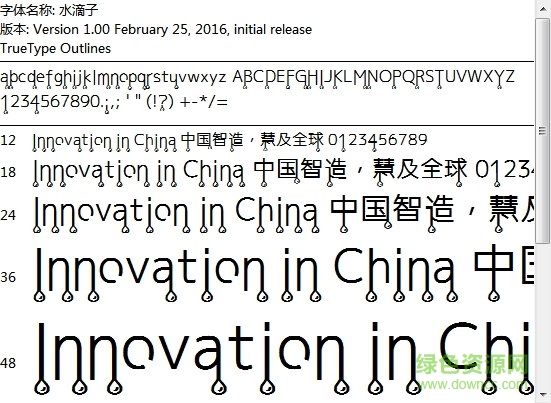
水滴子字體
水滴子字體,全名甘參水滴子字體,是一款有著很多小水滴圖案的卡通字體,精致透明的小水珠讓你的文字也變得潤滑流動起來,十分可愛,快來綠色資源網(wǎng)試試吧!
甘參水滴子字體特色
綠色資源網(wǎng)小編點評
水滴子字體是不同于漢儀水滴體的一款藝術(shù)字體,深化了水滴的藝術(shù)形象,給你的文字增加了輕松可愛的點綴,適用于藝術(shù)設(shè)計、廣告策劃、活動海報等。